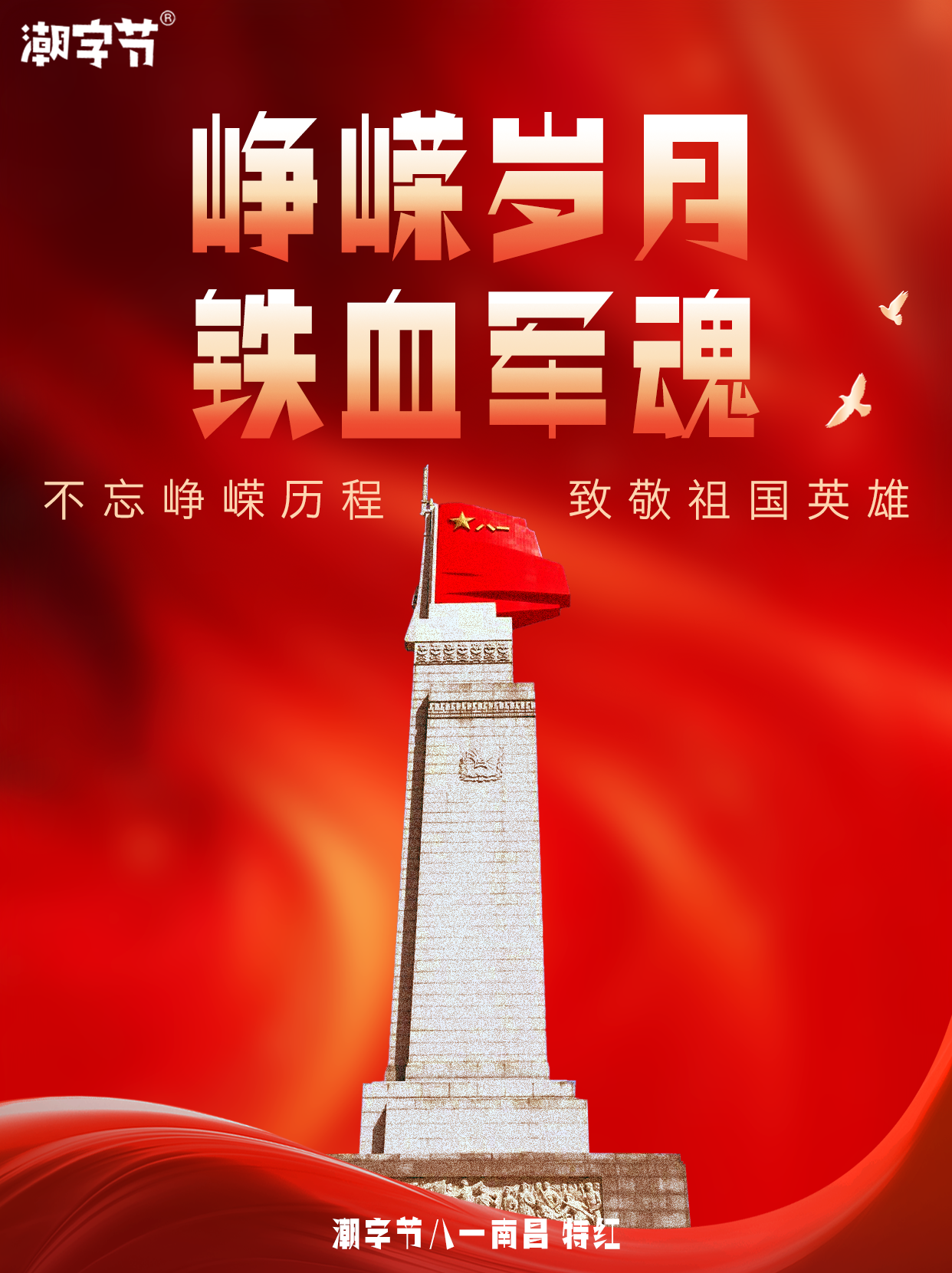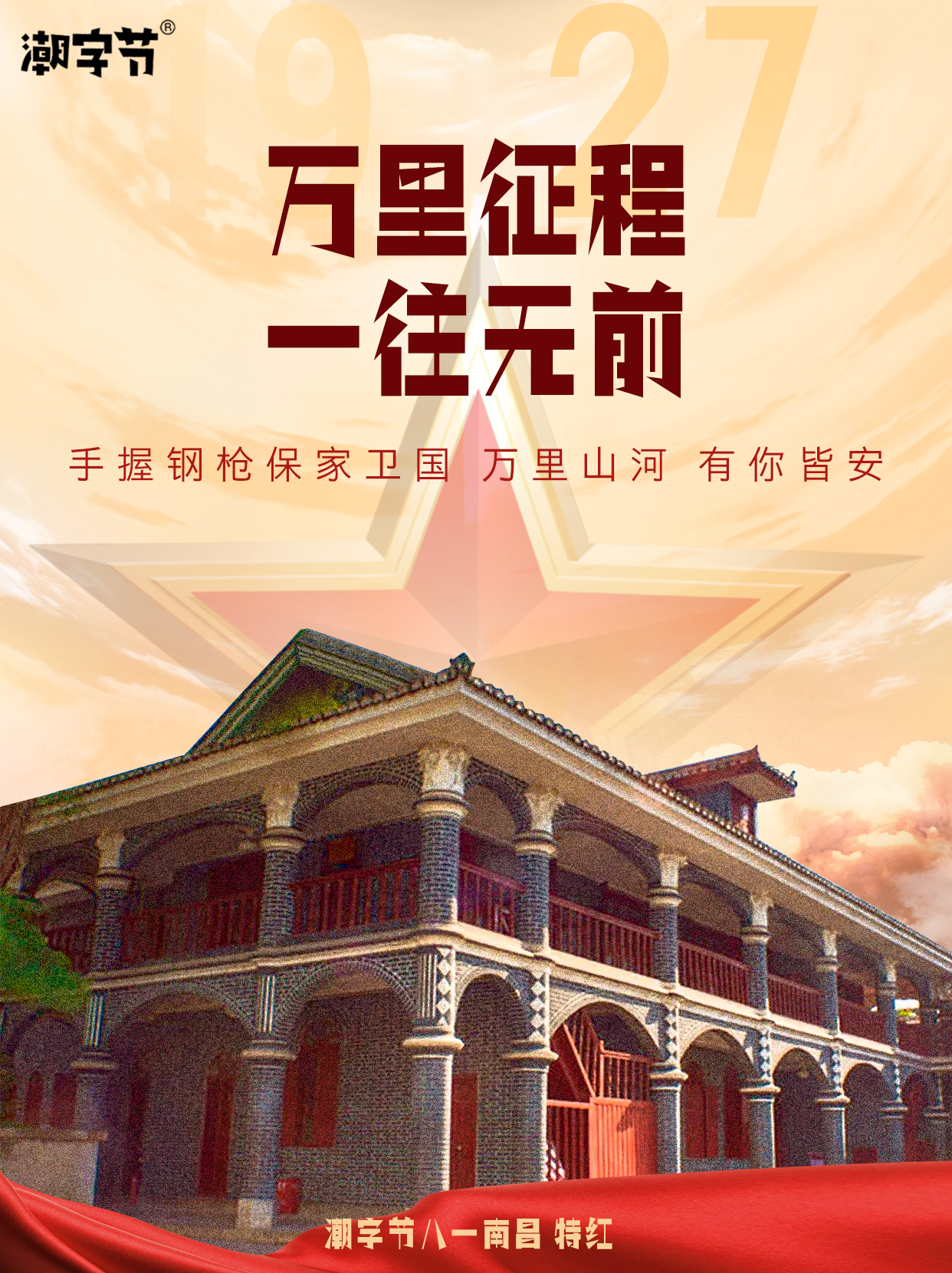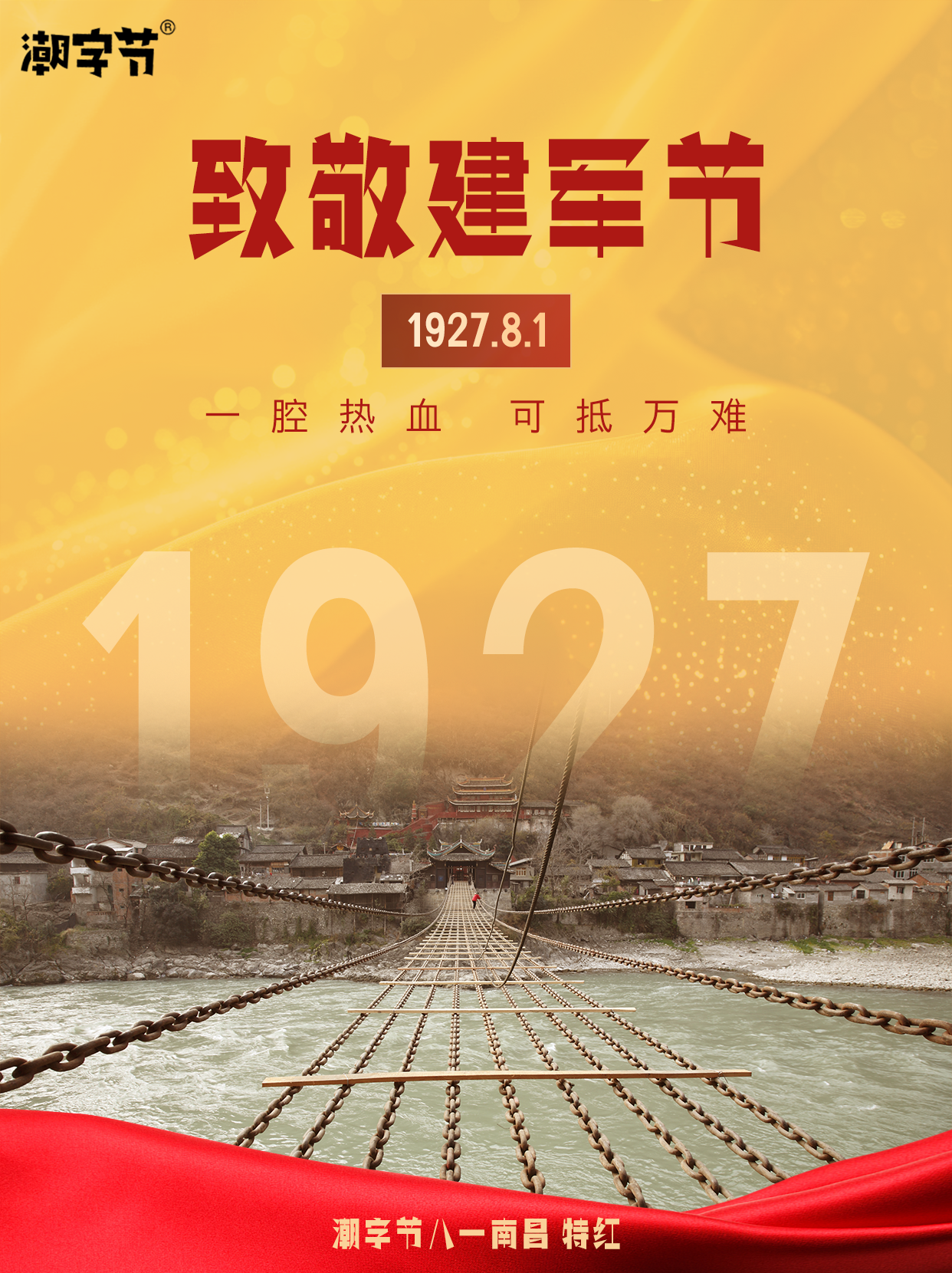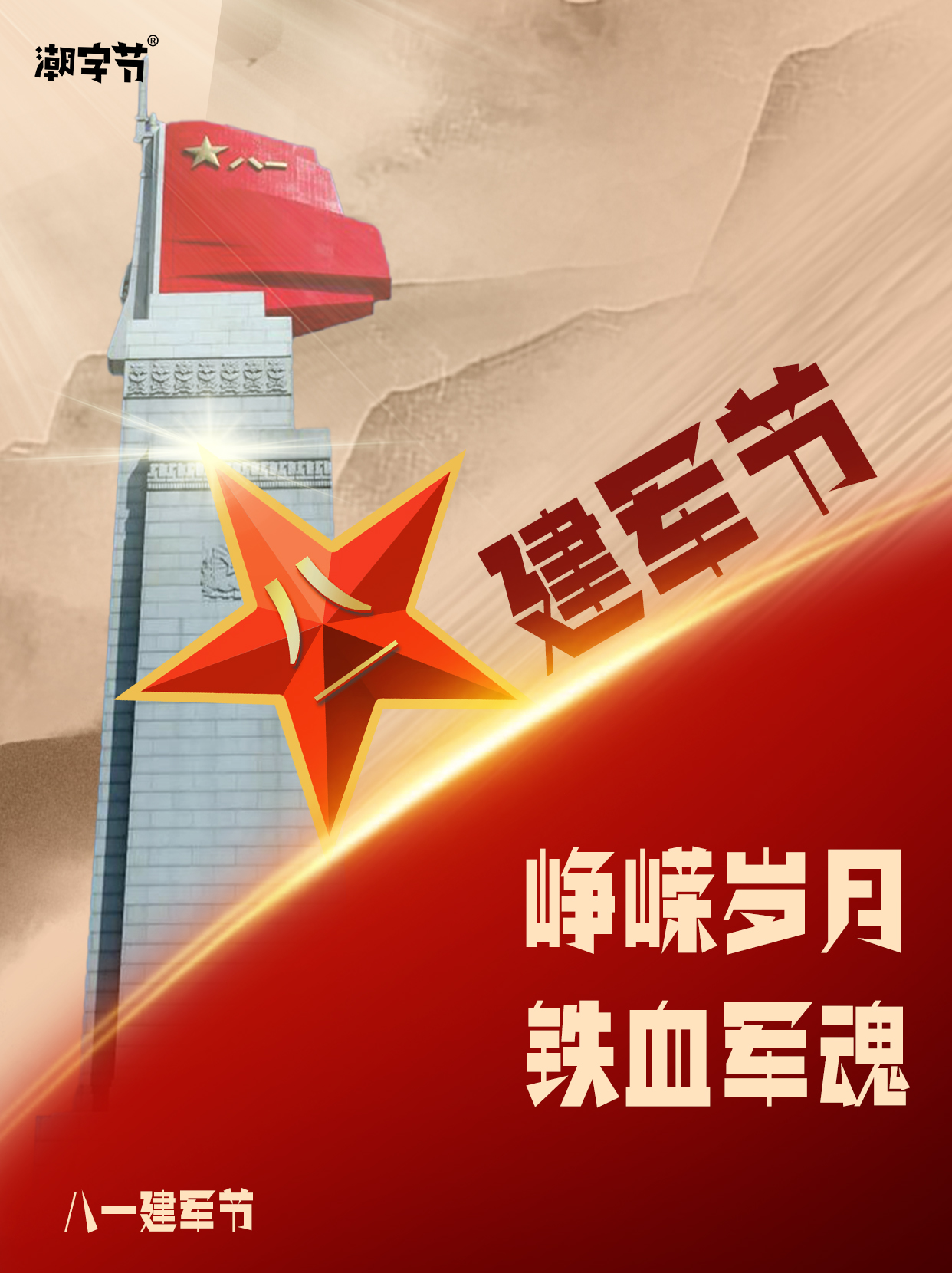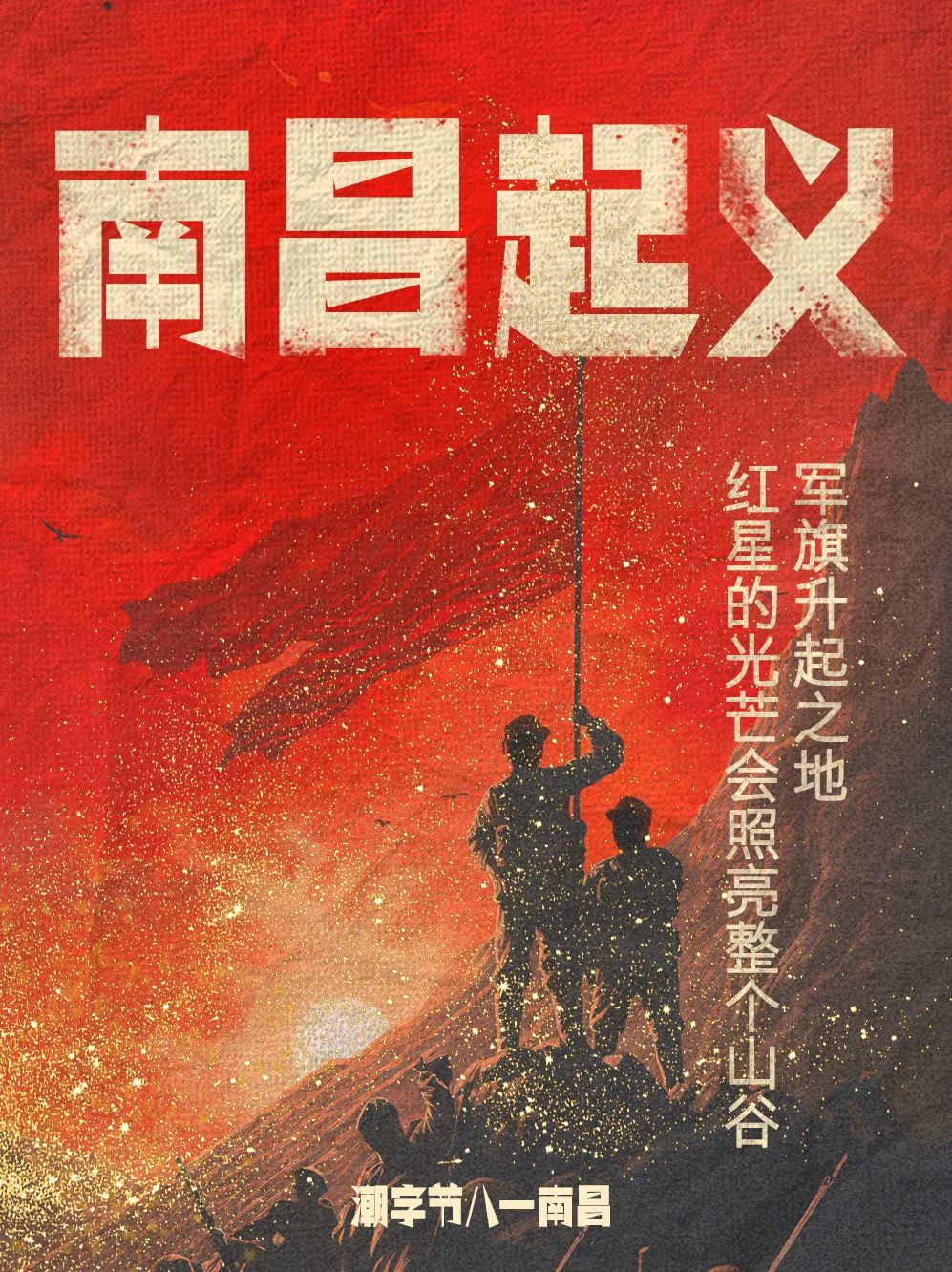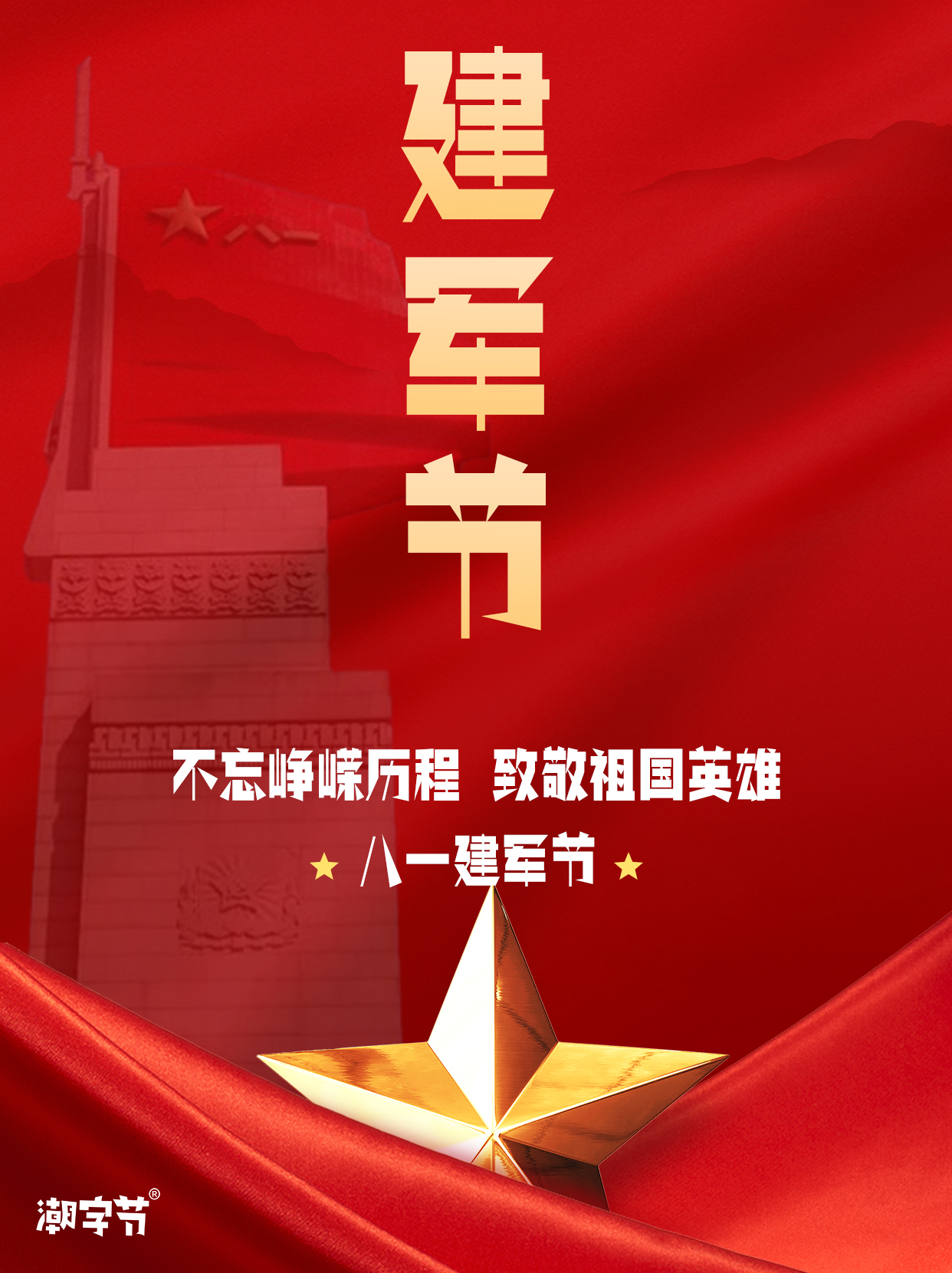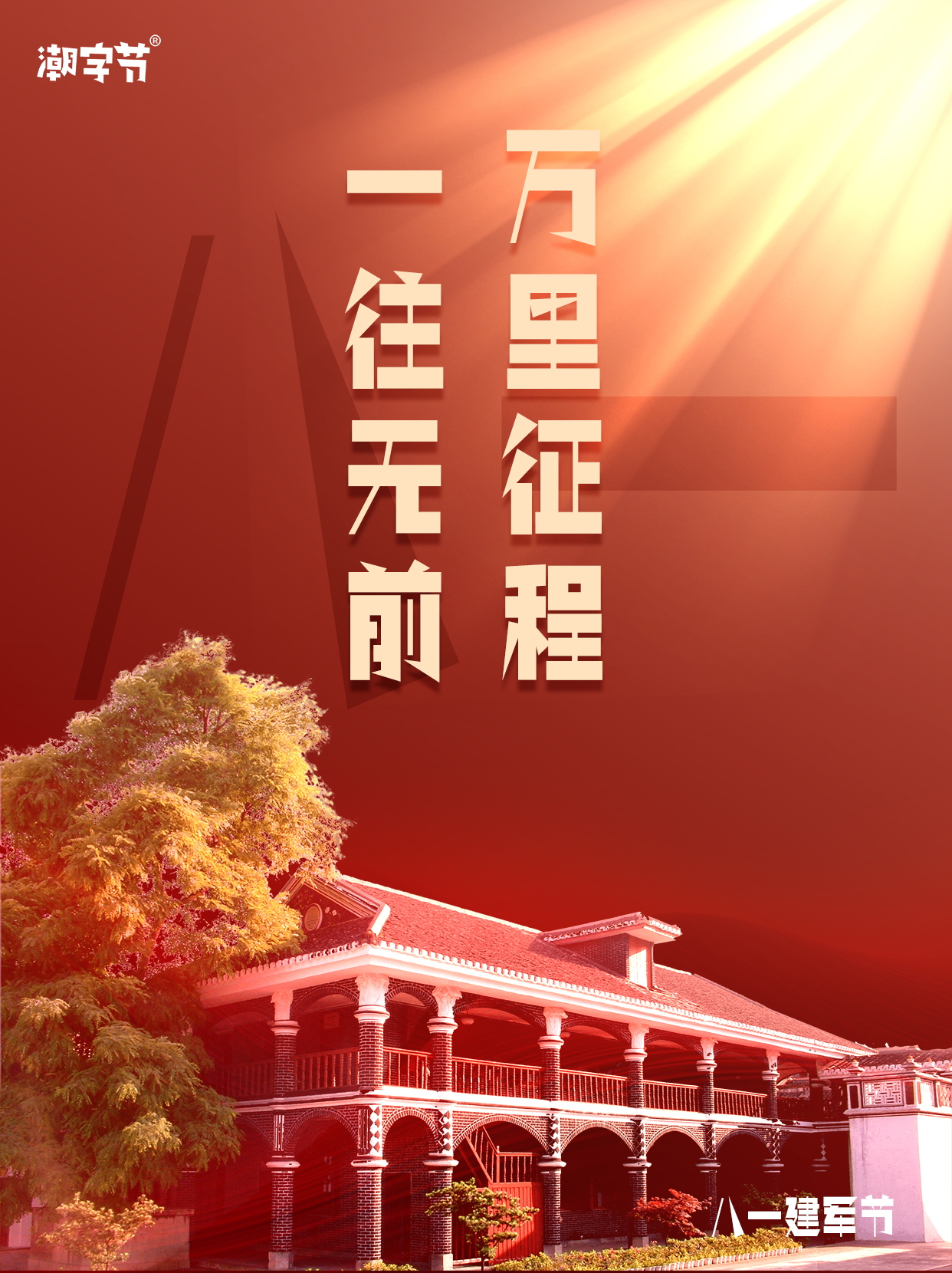
潮字节八一南昌 特红是一款具有鲜明的个性化的创意黑体,通过借鉴了民国设计先辈的几何构造尝试,形成独具特色,既复古又先锋的视觉体验。
字型整体略显窄长,横竖笔画粗壮,切口设计简洁现代,但通过线条、三角形尖锐的锥子形的几何构造笔画的点缀,突破了传统的黑体设计,非常适合用于品牌标识、广告和杂志与文化宣传等场合。